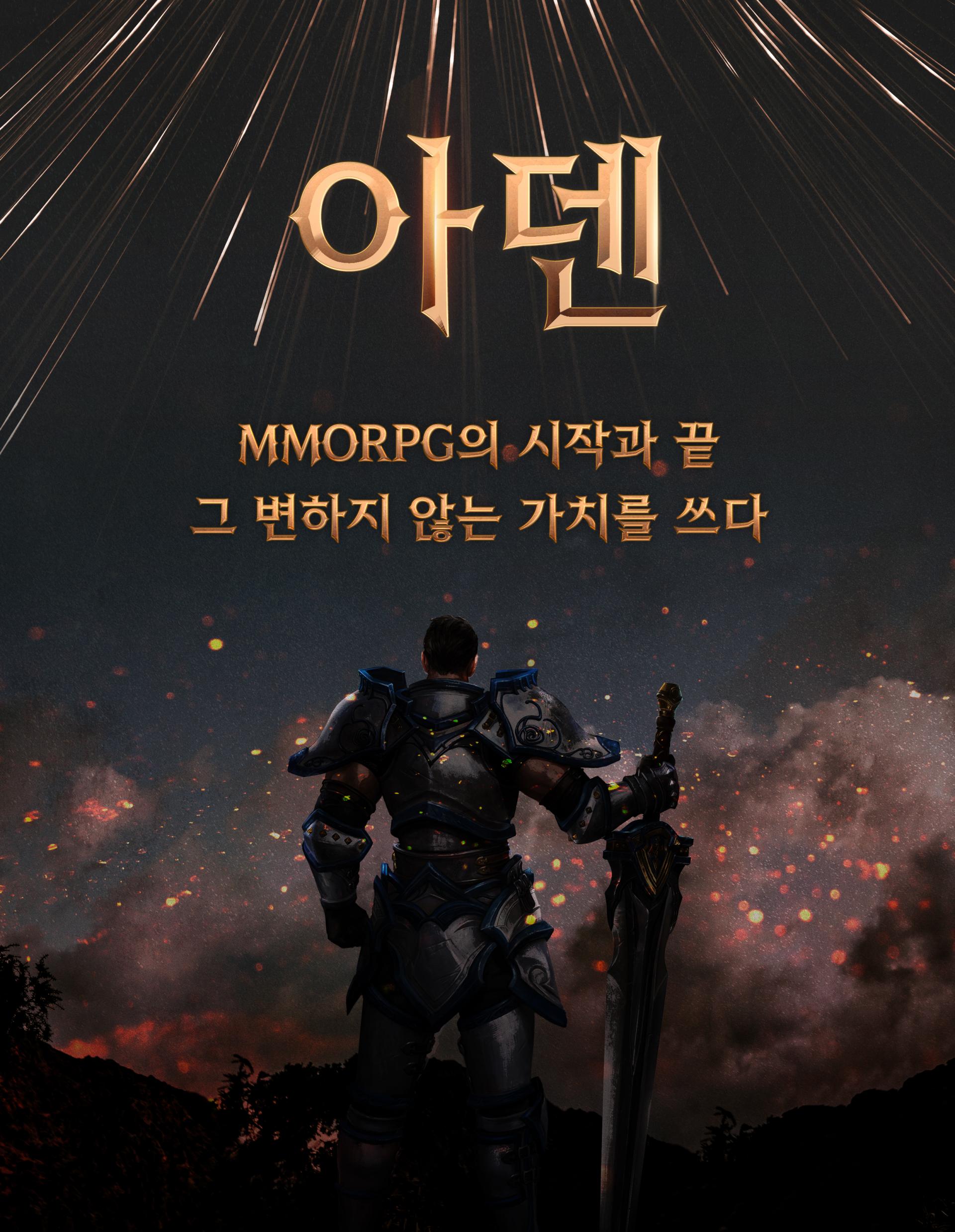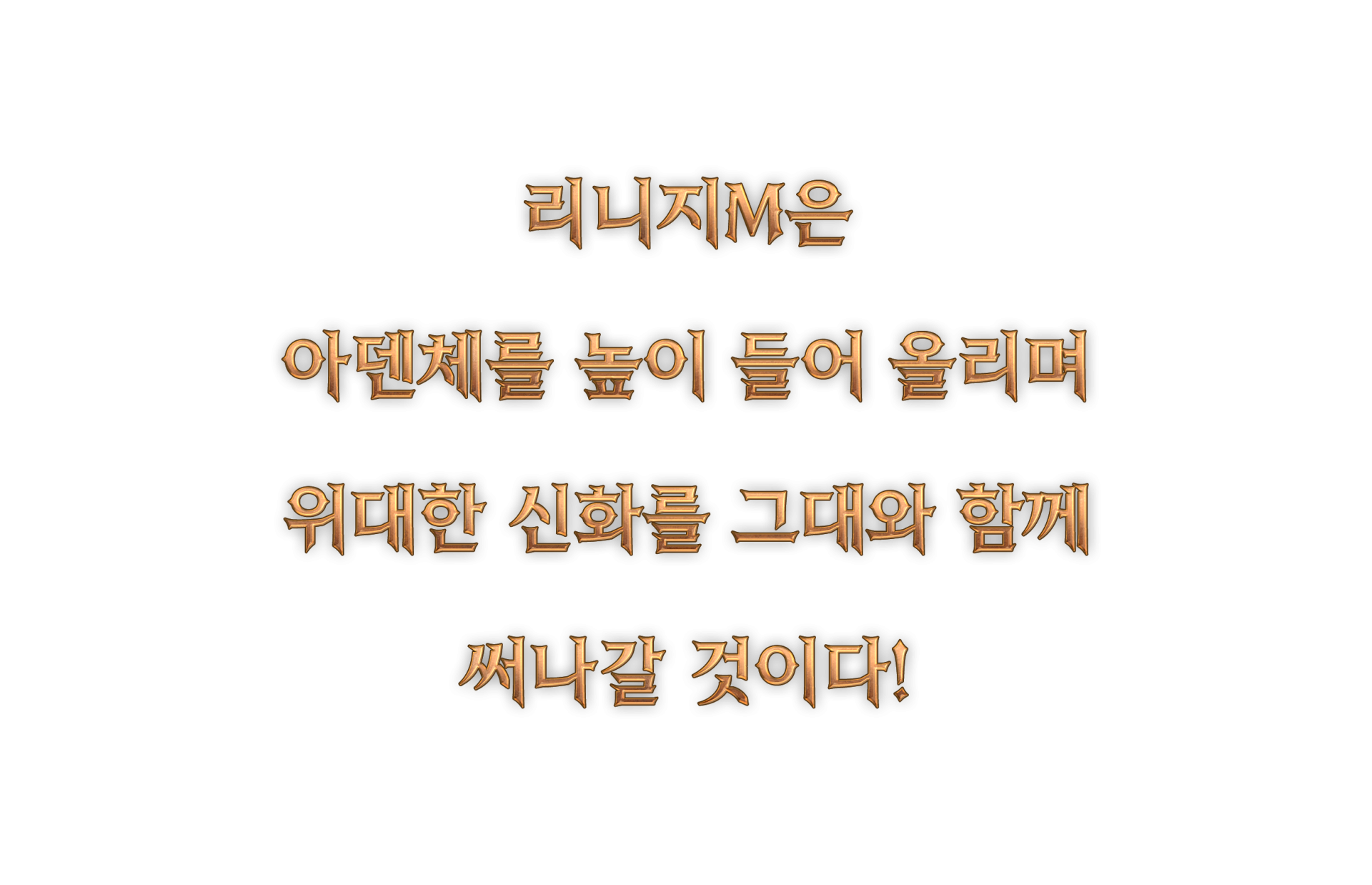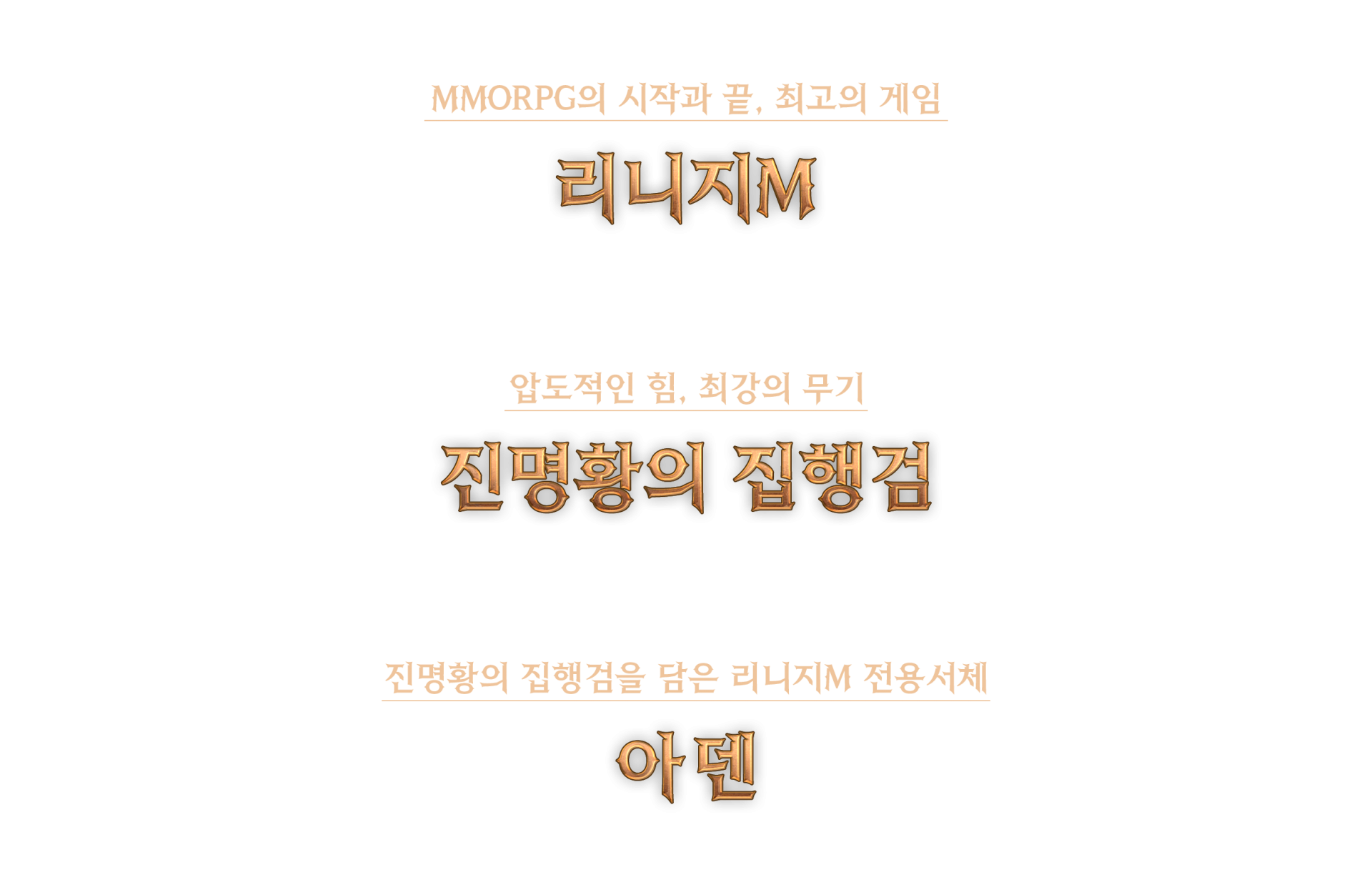
NCSOFT [리니지M]
엔씨소프트에서 개발한 리니지M 전용서체 '아덴체'는 최강의 무기, ‘진명황의 집행검’을 디자인 모티브로 삼아 치열한 공성전을 날카로운 형태로 시각화하였습니다. 자소와 세리프, 글줄에서 긴장감과 속도감을 느낄 수 있고, 섬세한 두께 조절로 날렵한 느낌을 줍니다. 단단하고 견고한 글자의 형태로 가독성을 높이고 디테일은 살려 디자인했습니다.